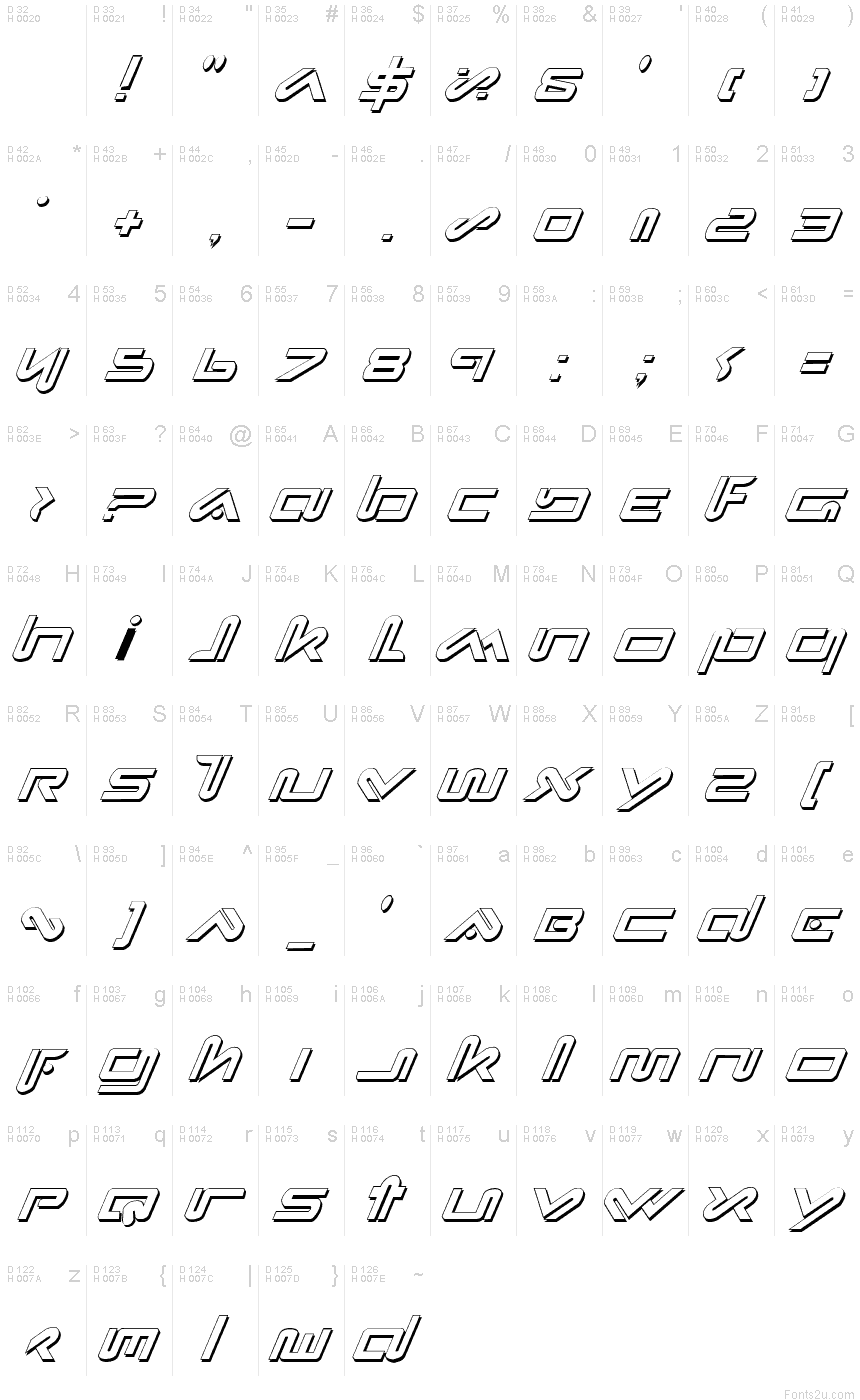
Xephyr Shadow Italic von Iconian Fonts ist eine kostenlose, futuristische Display-Schrift mit einem eleganten Sci-Fi-Touch. Die Buchstaben neigen sich in abgerundeten, röhrenartigen Strichen nach vorn, während ein harter Schattenwurf darunter für den unverwechselbaren Tech-Logo-Look der frühen 2000er sorgt – ohne dabei ihren fließenden, fast aerodynamischen Rhythmus zu verlieren.
Die Schrift eignet sich perfekt für Gaming-Logos, Flyer für elektronische Musik, Plakattitel, Cover-Texte und Title Cards, bei denen Bewegung im Schriftbild gefragt ist. Setzen Sie Xephyr Shadow Italic ein, wenn kurze Wörter, Brandings oder Monogramme schnell und synthetisch wirken sollen, denn die angewinkelten Formen und der abgesetzte Schatten erzeugen Tiefe, noch bevor Sie Effekte hinzufügen.